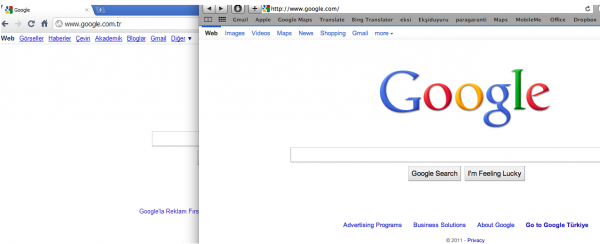
mac os x font sorunu
şimdi biz hayırlısı ile macbook air e taşındık ama ekte fotoda görüldüğü gibi içinde kurulu virtualbox ta çalışan chrome vb. tüm windows uygulamalarındaki fontlar sanki mac in fontlarından daha keskin ve daha iyi okunur durumda. mac in kullandığı yazıtipi sanki kalın ve gölgeli gibi varmıdır bunun çaresini bilen ?
bu bir sorundan çok mac'in özelliği. hatta pek tercih edilmez o keskinlik windows'ta bir süre sonra göz yorduğu için. desktop'da sağ tıklayıp ayarlara girdiğinde cleartype açma sekmesi olması lazım, cleartype'ı açınca mac os gibi görünür fontlar windows'ta.
System Preferences -> Appearance -> Font Smoothing
Burdan font smoothing i kapatabilir, veya font boyutuna göre ayarlayabilirsin.